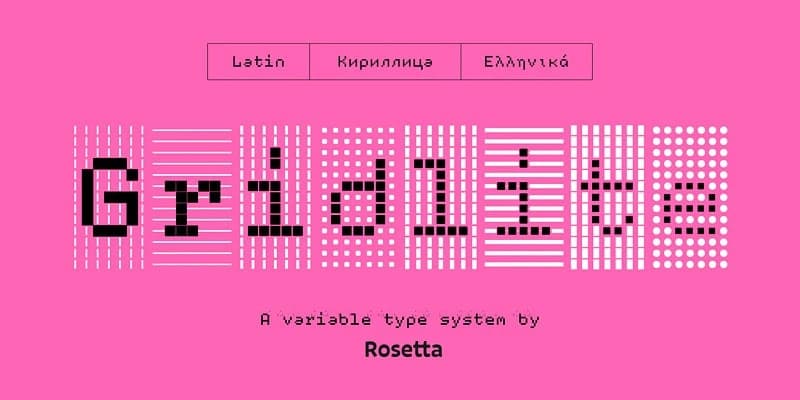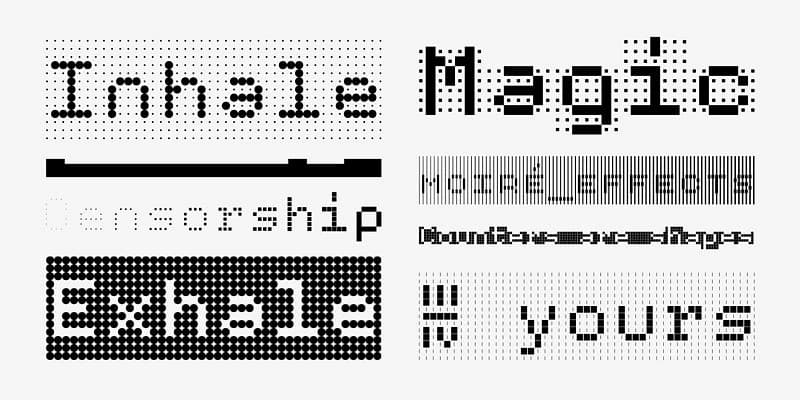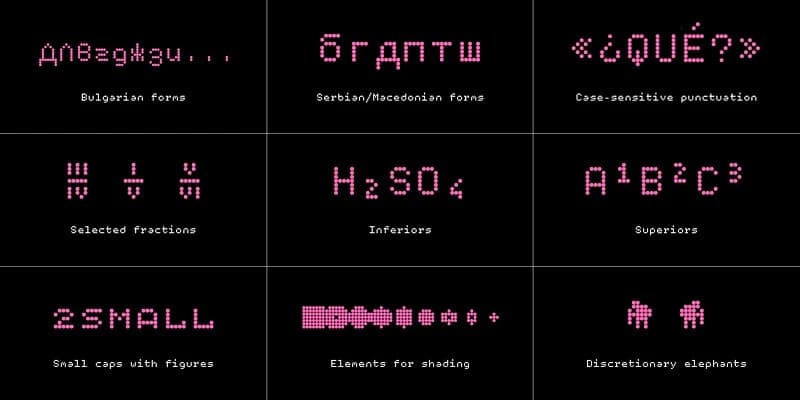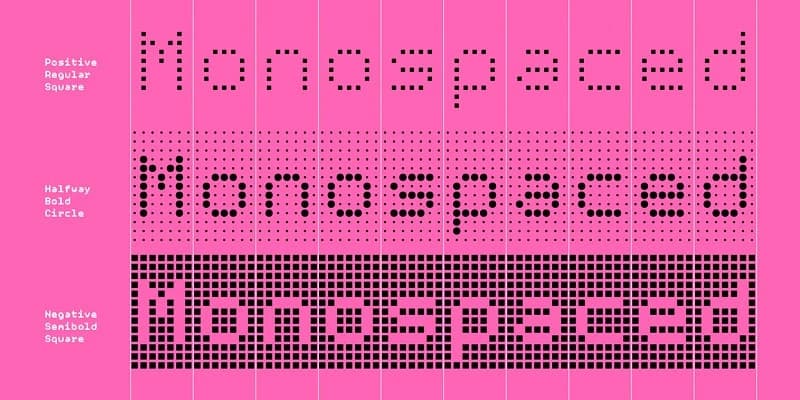
Gridlite PE Variable Font
Gridlite PE Variable Font, modüler bir ızgara sistemi üzerine kurulu, modern ve deneysel bir gösteri yazı tipidir; monospaced yapısıyla belirgin bir piksel benzeri, dijital estetik sunar. Değişken font teknolojisi, şekil, kalınlık ve arka plan üzerinde esnek ayarlamalara olanak tanır, böylece dinami
Gridlite PE Variable Font modern, deneysel bir gösterim yazı tipidir; modüler bir ızgara sistemi üzerinde kurulu, monospaced yapıda ve kendine özgü piksel benzeri, dijital bir estetiğe sahiptir. Değişken yazı tipi teknolojisi, biçim, kalınlık ve arka plan üzerinde esnek ayarlamalara olanak tanır ve dinamik ve özelleştirilebilir tipografi sağlar.